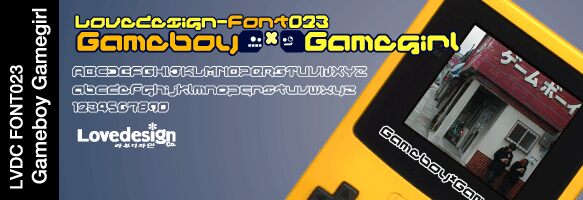
Gameboy Gamegirl di Wataru Osakabe è un font display futuristico gratuito che cattura la nostalgia delle console portatili con un tocco moderno e raffinato. Le sue lettere spesse e arrotondate, gli angoli interni netti e i contorni decisi ricordano le cartucce dei videogiochi, conferendo al testo una presenza amichevole ma tecnologica. Il ritmo è compatto e continuo, rendendo le parole simili a un logo connesso uscito direttamente da una schermata di avvio retrò.
Grazie a Gameboy Gamegirl, titoli e loghi acquisiscono immediatamente un'energia giocosa ispirata alle sale giochi, pur mantenendo un aspetto pulito e professionale. Questo font gratuito è perfetto per titoli di giochi, overlay per streaming, branding per e-sport, grafica per merchandising, poster di eventi e menu dell'interfaccia utente audaci. Usalo in dimensioni grandi per esaltare il contorno e abbinalo a un sans serif geometrico semplice per il testo principale, mantenendo così un aspetto coeso e leggibile.